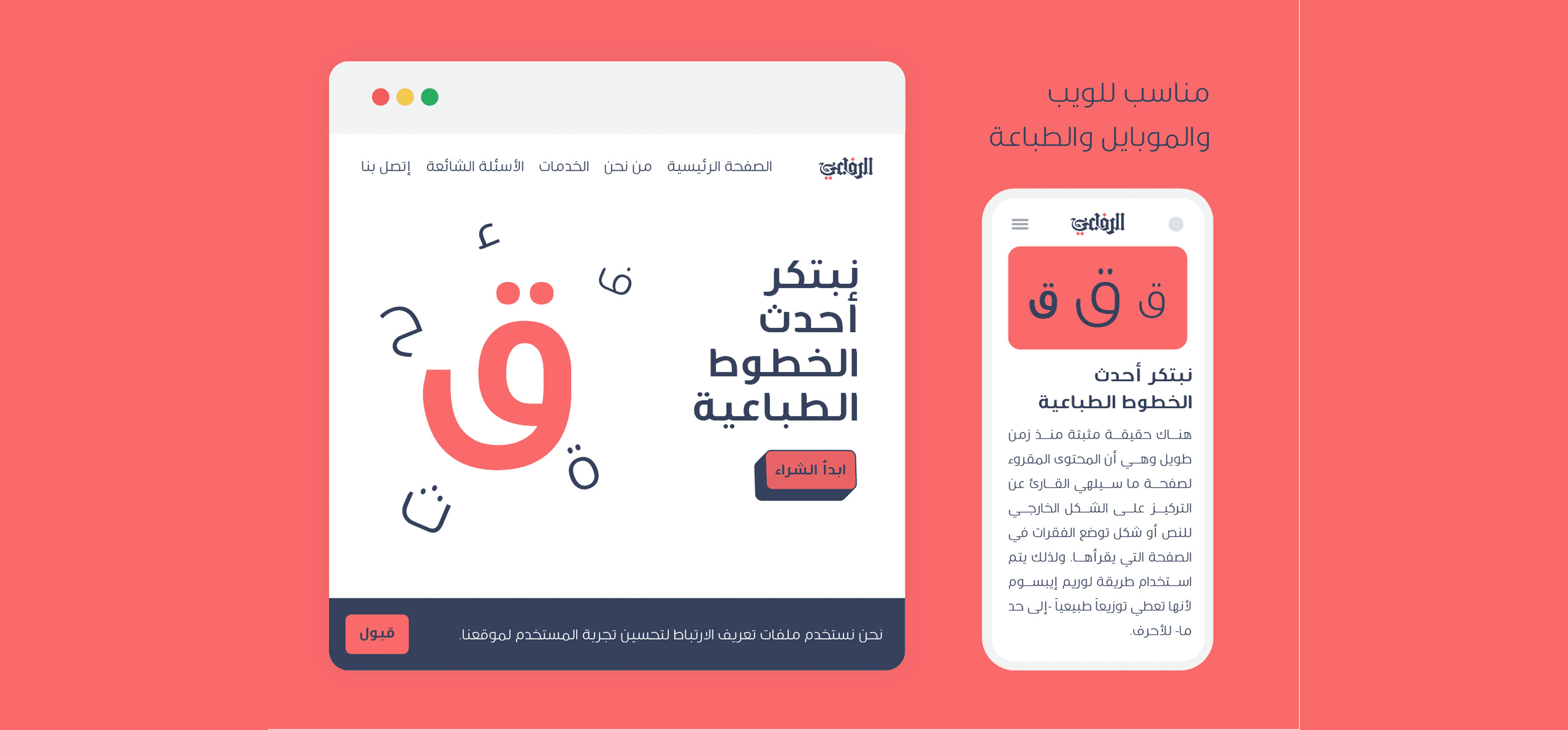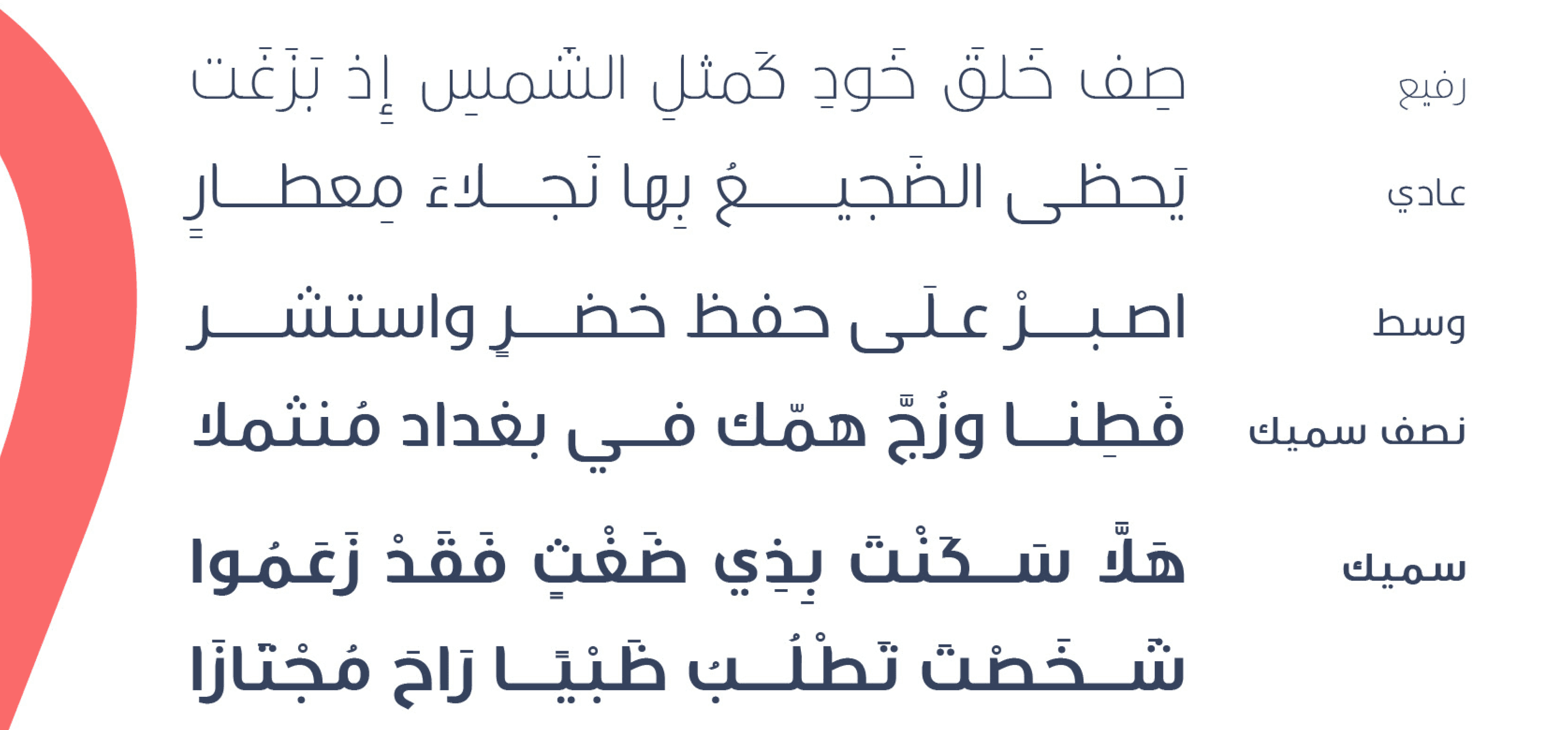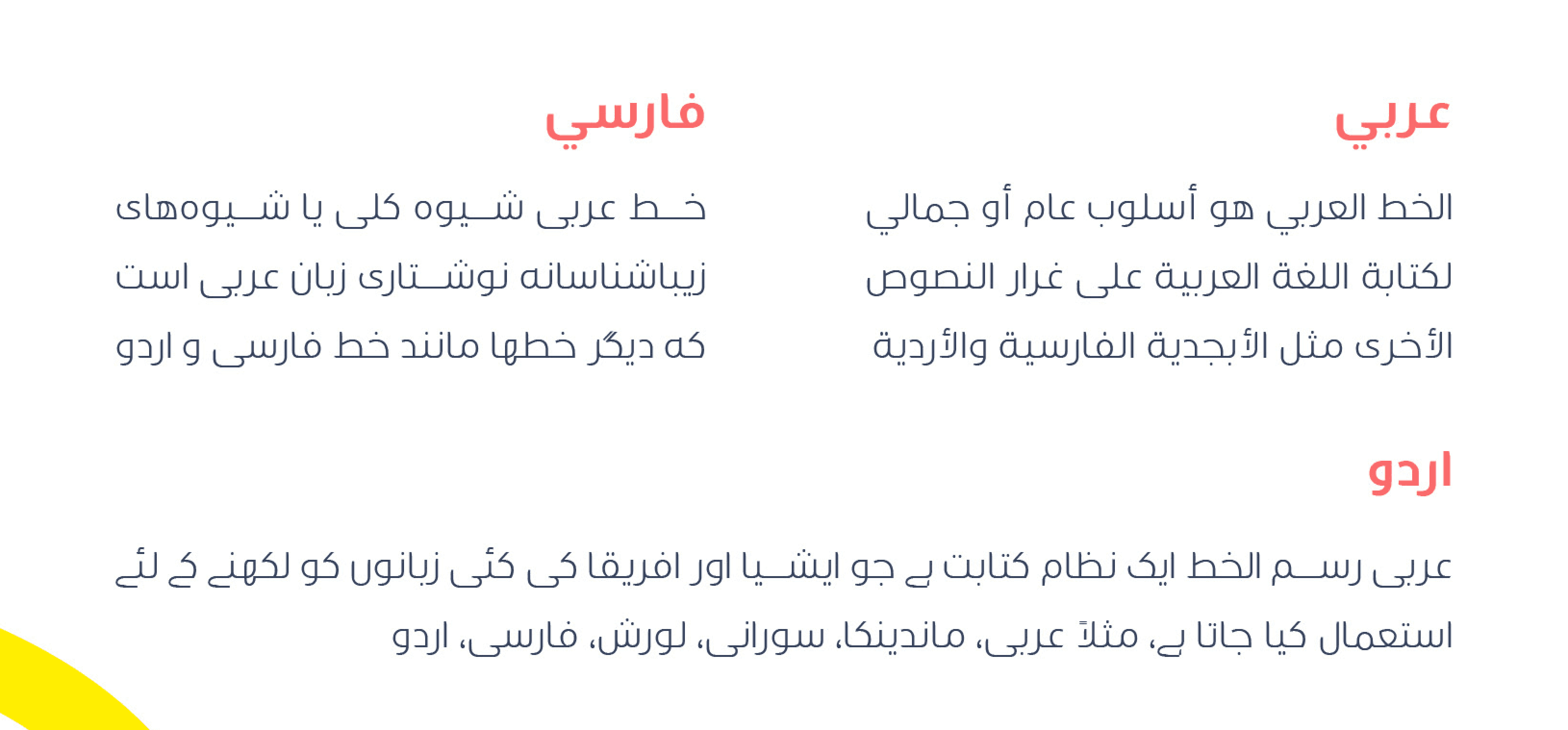
خط YR Qaf هو خط نظيف، عصري، وعالي الوضوح. يتميز بأشكال حروف واضحة وسهلة القراءة مع تركيز كبير على قابلية القراءة. صُمم الخط بعناية من خلال تحقيق توازن دقيق في التناسق بين الأشكال، مع إبراز الخطوط الرأسية، مما يمنحه مظهرًا متناسقًا وانسيابيًا.